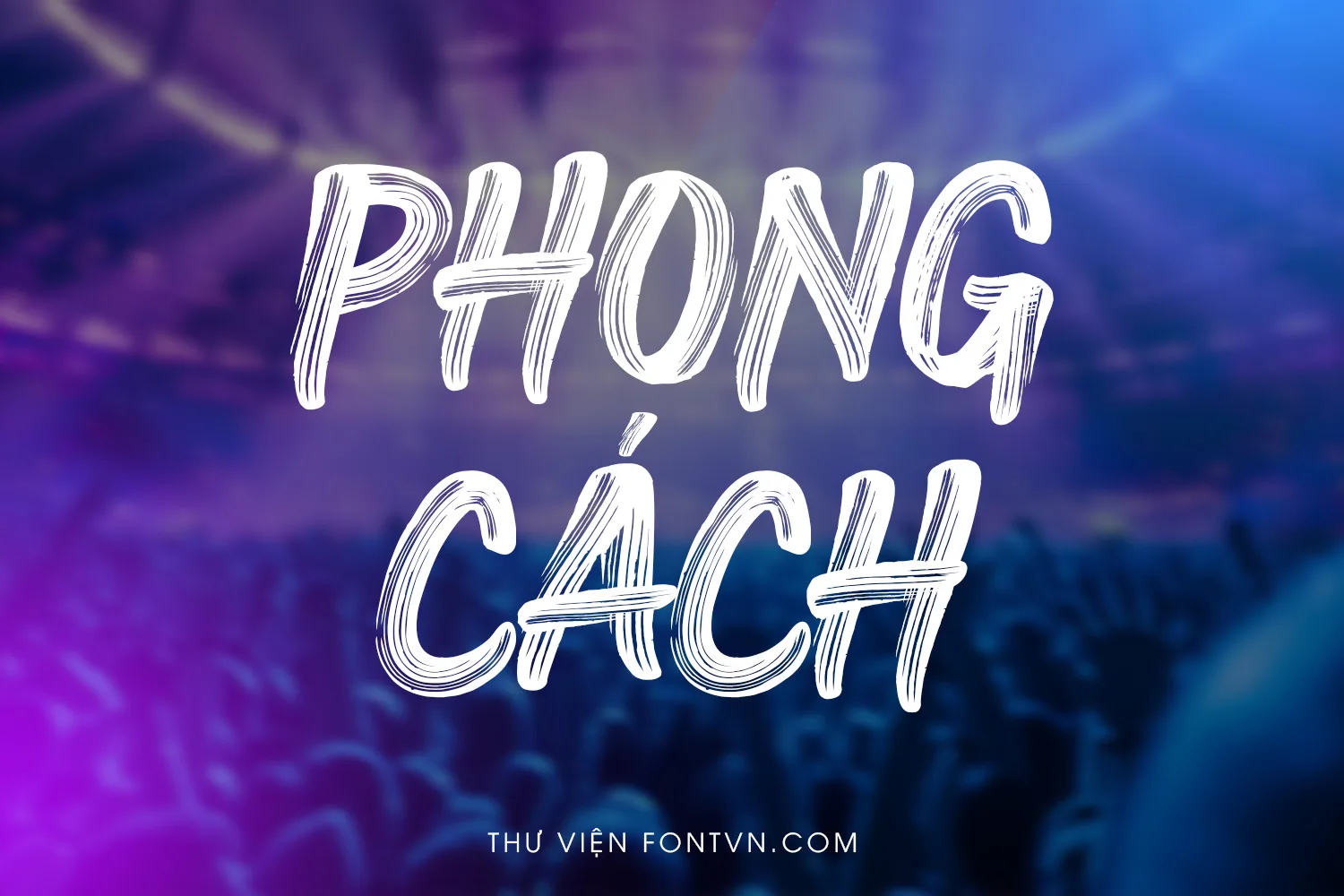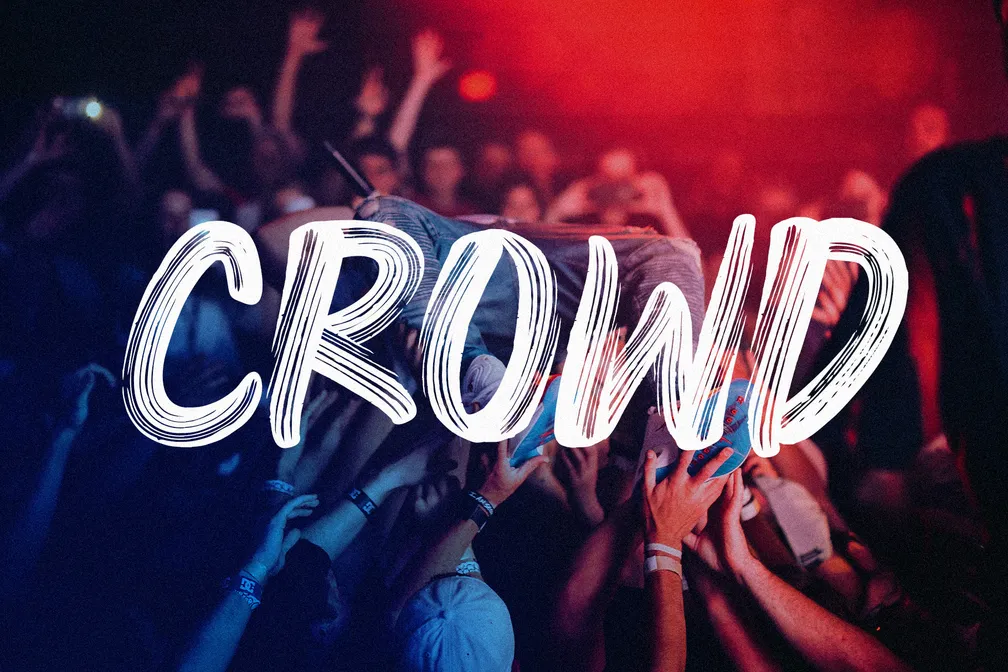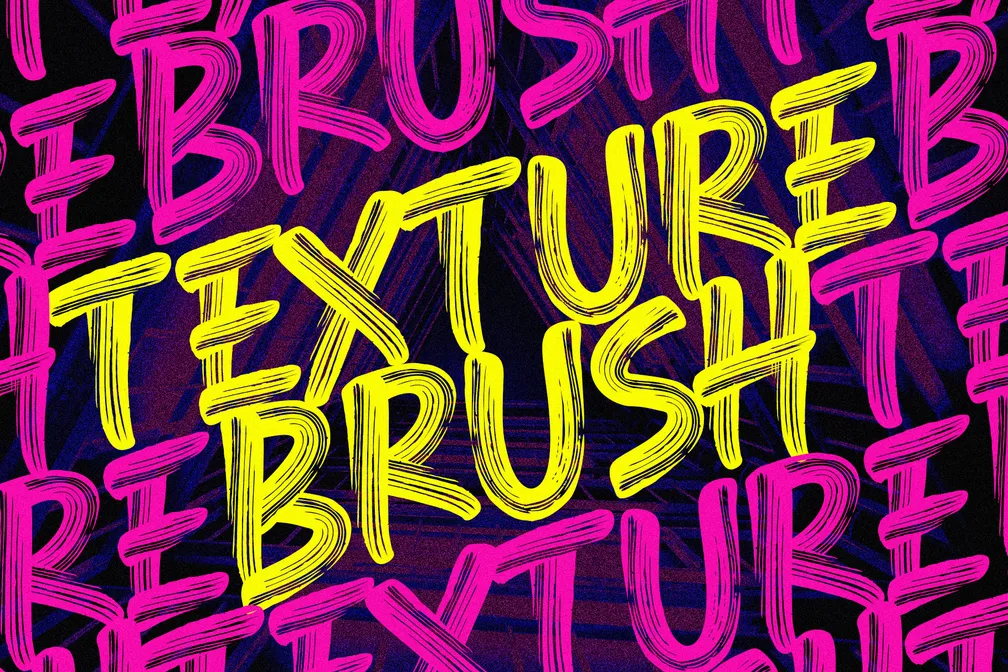
DVN – Brush Line là một phông chữ mang phong cách thư pháp (brush font) đầy mạnh mẽ, sinh ra để dành cho những thiết kế cần sự bứt phá. Với những đường nét mô phỏng vết xước chân thực của cọ mực, phông chữ này mang đến cảm giác chuyển động dồn dập, thô ráp nhưng cực kỳ phóng khoáng.